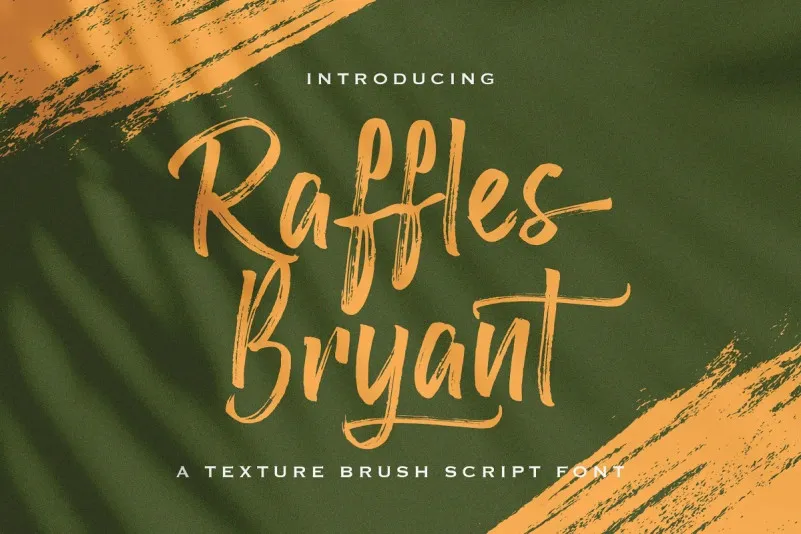
A fonte Raffles Bryant é uma opção elegante para designers em busca de texturas autênticas e contemporâneas. Cria-se por meio da StringLabs, oferecendo um design moderno que traz consigo um encantador e leve sentimento. Perfeito para aplicar um toque natural às suas criações, esta fonte é perfeita para jornais, posters, identidades visuais, convites, fotografia, marcas impressas, assinaturas de sites, logotipos, cartões de visita e outros produtos de design. Com seu estilo confortável e charmoso, Raffles Bryant enriquece seus projetos ao proporcionar um toque agradavelmente autêntico. Quebre o monótono dos designs digitais com uma dose de realismo fornecida pela fonte Raffles Bryant da StringLabs.